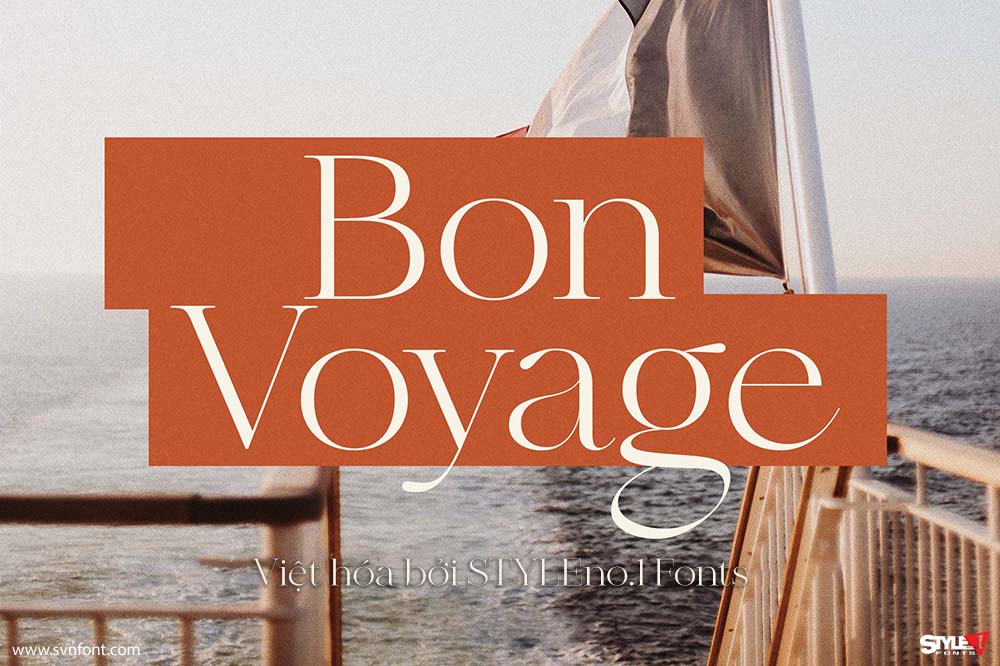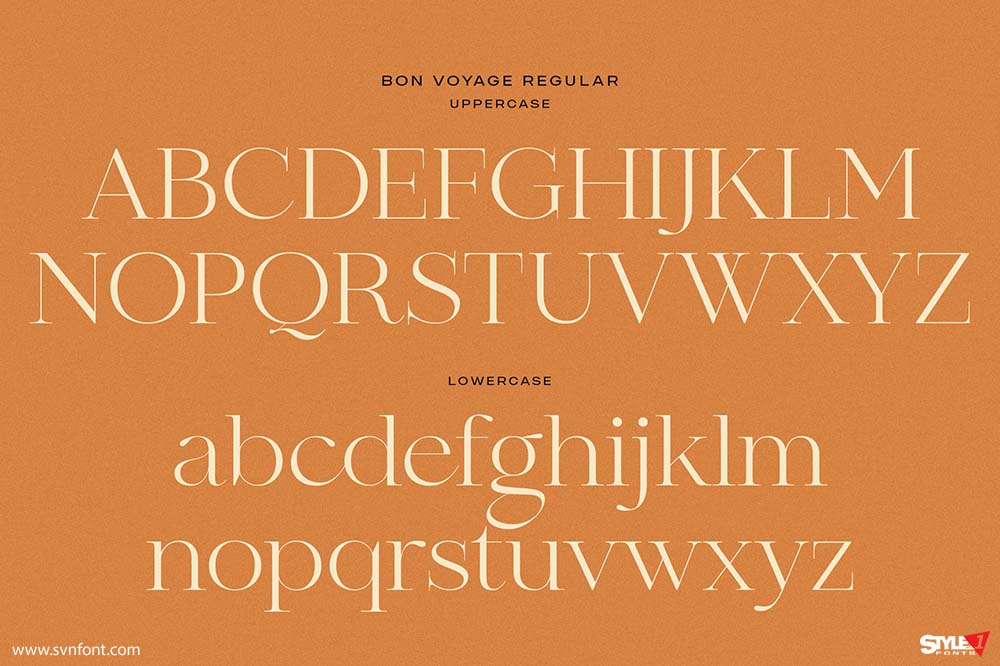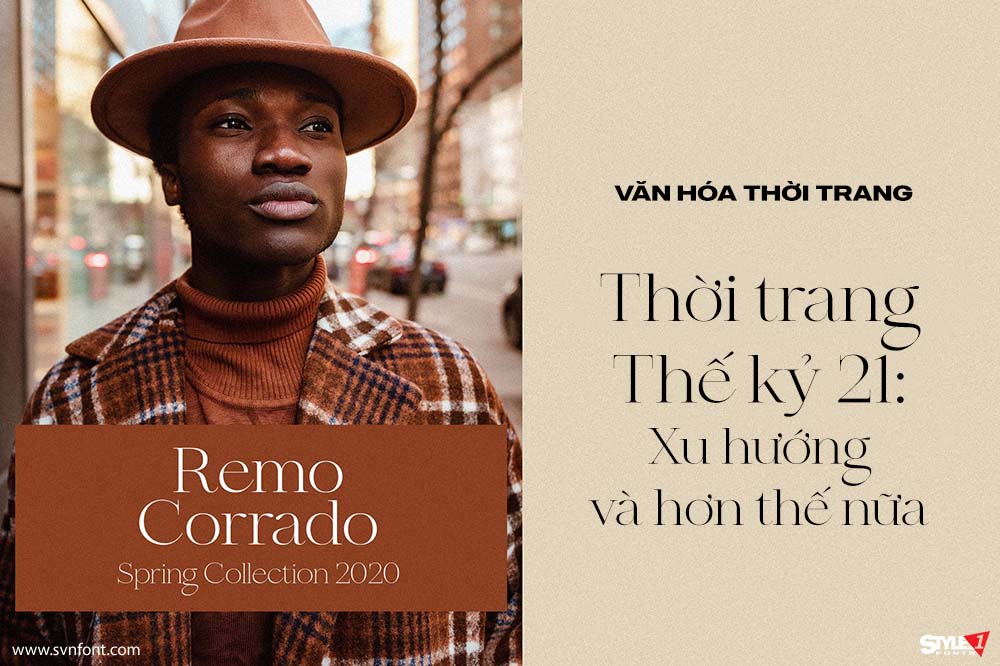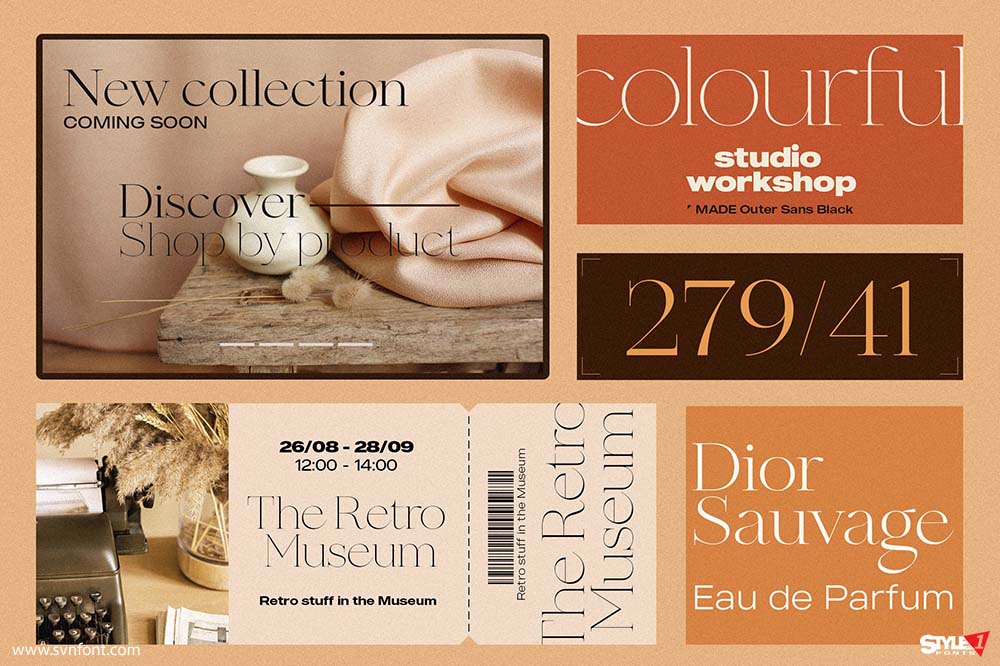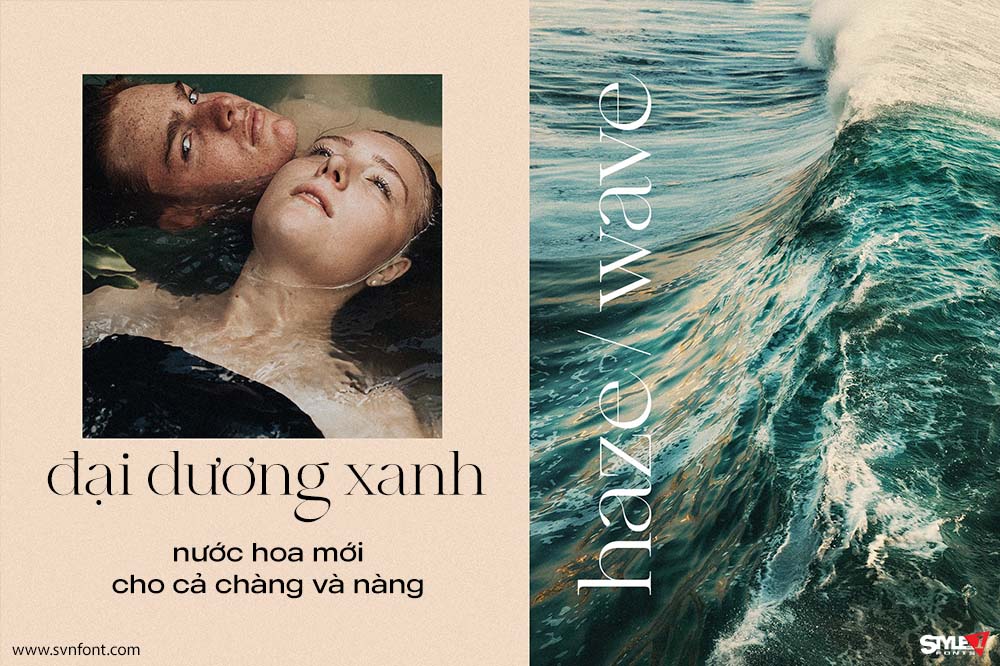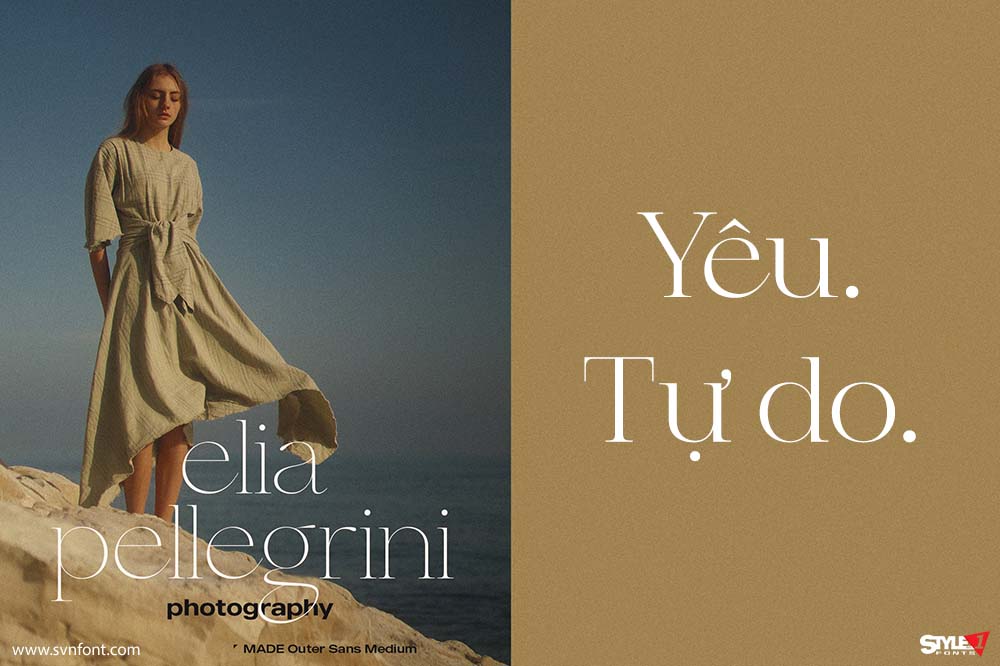
Font Việt Hóa SVN -Bon Voyage Mang Phong Cách Hiện Đại, Thanh Mảnh
Bon Voyage, là một serif font hiện đại. Font phù hợp cho thiết kế về quảng cáo, tạp chí, thời trang...